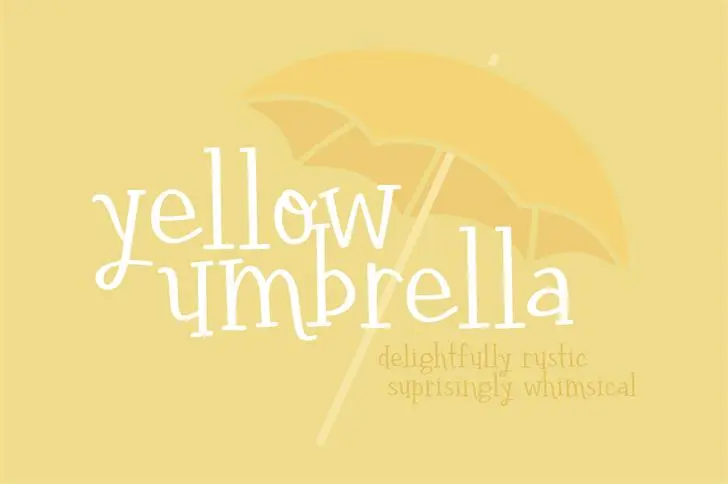
A Yellow Umbrella Font é uma serifada elaborada a mão, projetada por Hamilton. Esta fonte traz um ar quase descontraído à sua arte e design, especialmente adequada para trabalhos que exigem um toque de rusticidade leve e amigável. Sua forma densa e detalhada dá-lhe um brilho especial sem perder a elegância, perfeita para projetos de crafts ou qualquer projeto onde um pouco de rusticidade se encaixa naturalmente no design. Ideal para aqueles que buscam uma fonte serifada com certa leveza, a Yellow Umbrella Font é como um guarda-chuva amarelo: levemente protetor e cheio de vida.